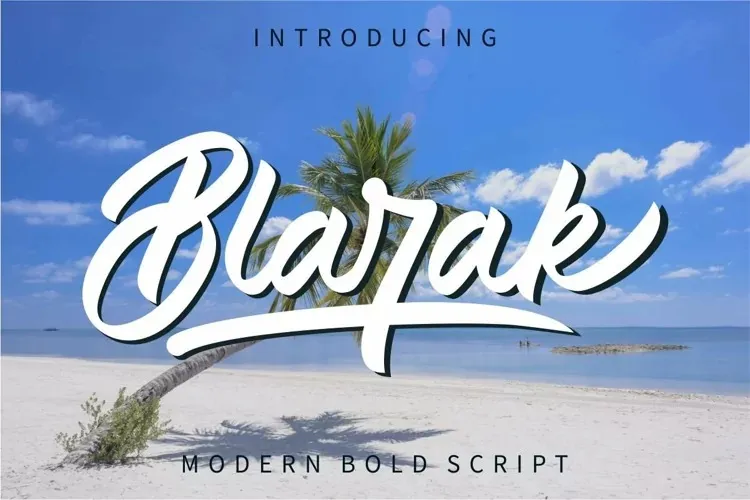
Blarak é uma fonte cursiva e vintage inspirada em escrita manuscrita, projetada pelo incrível GFR creative para diversos usos criativos. Suave e elegante, Blarak oferece um estilo atraente que se destaca em muitas aplicações. Perfeita tanto para criação de logomarcas e identidades corporativas como para design fotográfico, convites, marcas de água, anúncios, embalagens, materiais de papelaria, projetos de casamento, rótulos ou embalagens especiais. Uma das coisas únicas que fazem Blarak tão interessante é sua disponibilidade para caracteres minúsculas com traços. Este recurso permite uma flexibilidade incrível na criação e personalização da fonte. Para aqueles que preferirem usar a fonte em programas como Photoshop ou Illustrator, essa característica facilita ainda mais o acesso à opção de uso do traço. Blarak é perfeitamente adequada para qualquer projeto onde um toque autêntico e handwritten seja desejado. Seja para uma simples etiqueta de produto ou um design impressionante que destaca a personalidade da sua marca, Blarak estará sempre pronta para se adaptar às suas necessidades.